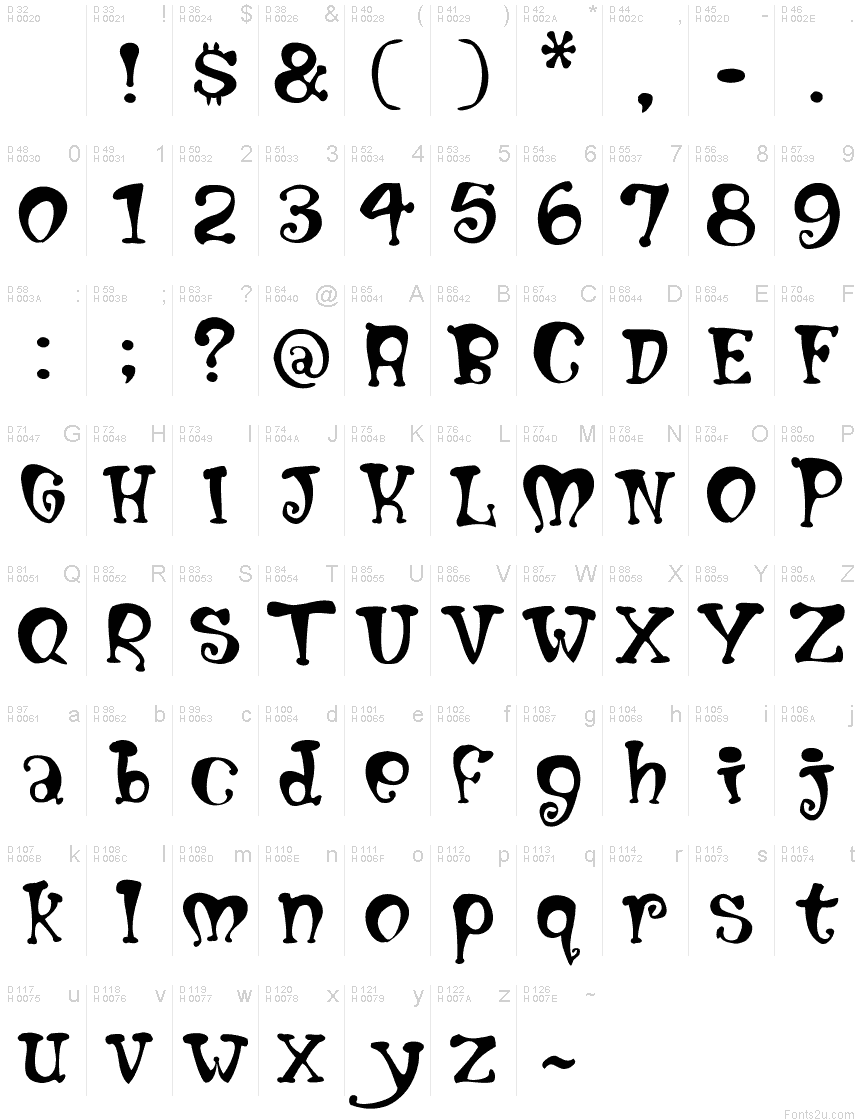
Mumblypegs od St Rachan Typeworks dla Fulongo to darmowy, rysunkowy krój pisma typu display z pękatymi krzywiznami, wąskimi łączeniami i kroplowatymi zakończeniami, które nadają literom odręczny, bajkowy charakter. Kształty są obłe i lekko nieregularne, a kreski zwężają się, by po chwili rozszerzyć, co nadaje całości żywy rytm, unikając przy tym niechlujstwa.
Mumblypegs świetnie sprawdzi się na okładkach książek dla dzieci, w tytułach komiksów, na wesołych plakatach, w logotypach, na opakowaniach czy w krótkich napisach eventowych. Ten darmowy font wnosi zadziorny, wyrazisty klimat do projektów wymagających typografii z energią i charakterem, zwłaszcza gdy szukasz czegoś fantazyjnego w nagłówkach lub przyjaznego akcentu dekoracyjnego.
Mumblypegs